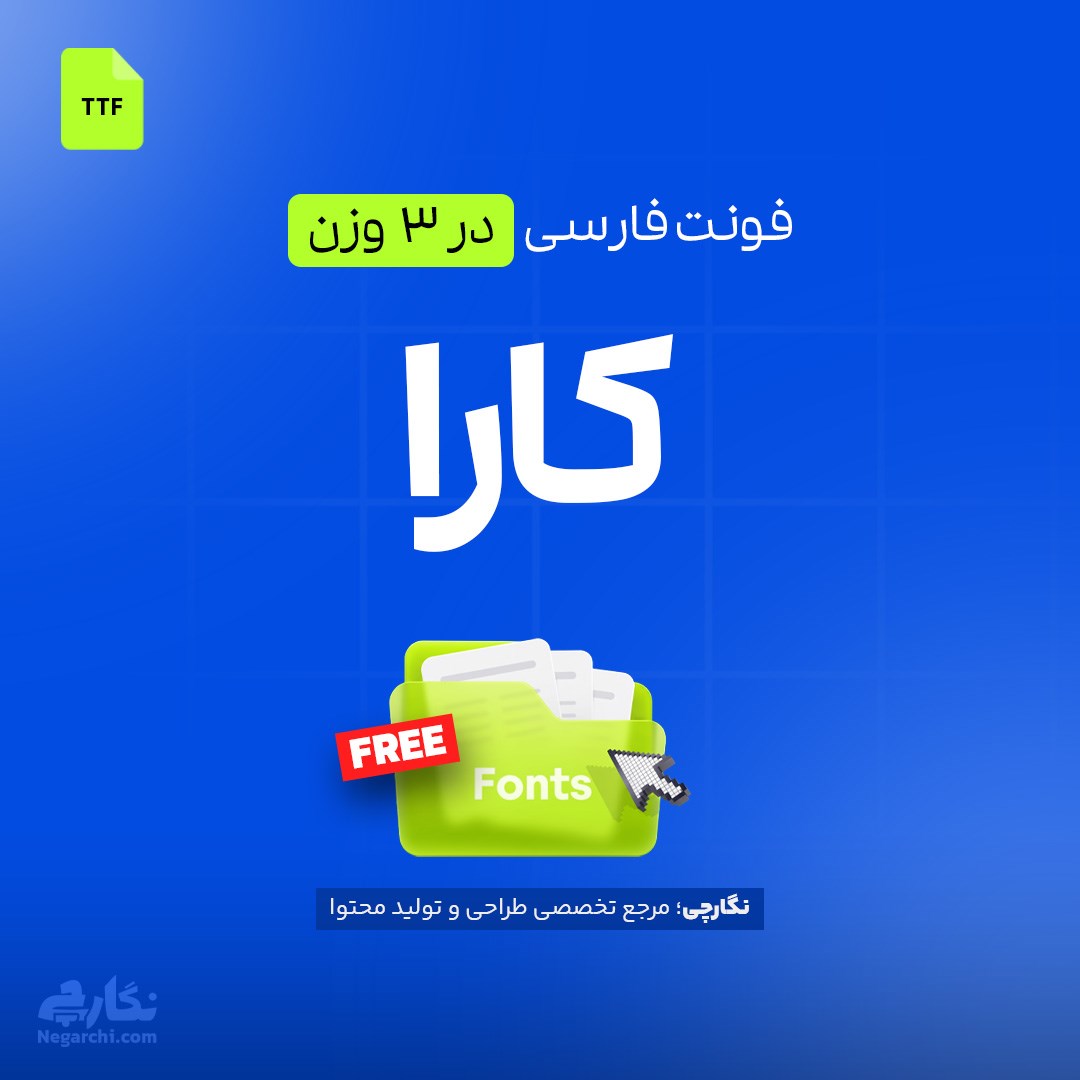
فونت فارسی کارا (Kara) یک تایپفیس متفاوت و کاربردی برای طراحی گرافیکی، متون طولانی، کتاب، مقاله و محتوای فارسی است که در سه وزن Light، Regular و SemiBold ارائه میشود.
فونت کارا (Kara) یکی از فونتهای فارسی با طراحی خاص و متفاوت است که برای استفاده در طرحهای گرافیکی و متون فارسی طراحی شده است. ساختار این فونت ظاهر متفاوت و خوانایی مناسبی دارد و در سه وزن Light، Regular و SemiBold ارائه میشود تا بتوان از ضخامتهای مختلف آن متناسب با نوع استفاده بهره برد.
فونت فارسی کارا با کیفیت طراحی بالا و ساختاری متفاوت، گزینهای مناسب برای پروژههایی است که به یک قلم فارسی متمایز و کاربردی نیاز دارند. این فونت در سه وزن Light، Regular و SemiBold قابل دریافت است و امکان استفاده از وزنهای مختلف را در طراحی و صفحهآرایی فراهم میکند.
فونت Kara در سه وزن Light، Regular و SemiBold ارائه شده است. وجود این سه وزن به طراح اجازه میدهد در بخشهای مختلف یک پروژه از ضخامت مناسب استفاده کند؛ برای مثال وزنهای سبکتر برای بخشهایی با ظاهر ظریفتر و وزنهای Regular و SemiBold برای متنها یا قسمتهایی که به تأکید بیشتری نیاز دارند.
فونت کارا در سه وزن Light، Regular و SemiBold ارائه میشود. این تنوع وزنی باعث میشود بتوان از Kara در بخشهای مختلف یک پروژه با ضخامتهای متفاوت استفاده کرد. وزن Light برای زمانی مناسب است که ظاهر ظریفتری مدنظر باشد و وزنهای Regular و SemiBold میتوانند برای متنهایی با تأکید بیشتر مورد استفاده قرار بگیرند. وجود سه وزن، فونت کارا را برای طراحیهای گرافیکی و همچنین صفحهآرایی متون فارسی کاربردیتر میکند.
بله، فونت Kara برای استفاده در متون طولانی، کتابها، مقالات و پروژههای صفحهآرایی فارسی قابل استفاده است. طراحی متفاوت این فونت در کنار ارائه سه وزن Light، Regular و SemiBold به کاربر امکان میدهد متناسب با ساختار متن، وزن مناسب را انتخاب کند. به همین دلیل فونت کارا فقط برای تیترهای گرافیکی کاربرد ندارد و میتوان از آن در پروژههایی که حجم قابل توجهی متن فارسی دارند نیز استفاده کرد.
بله، فونت کارا میتواند در انواع پروژههای گرافیکی و محتوای فارسی مورد استفاده قرار بگیرد. ساختار متفاوت و طراحی خاص Kara آن را برای طراحانی که به دنبال یک فونت فارسی متمایز هستند مناسب میکند. از این فونت میتوان در طراحی محتوای دیجیتال، صفحهآرایی، مقالات، کتابها و سایر پروژههایی که نیاز به تایپ فارسی دارند استفاده کرد و با انتخاب یکی از سه وزن موجود، ظاهر متن را با نیاز پروژه هماهنگ کرد.